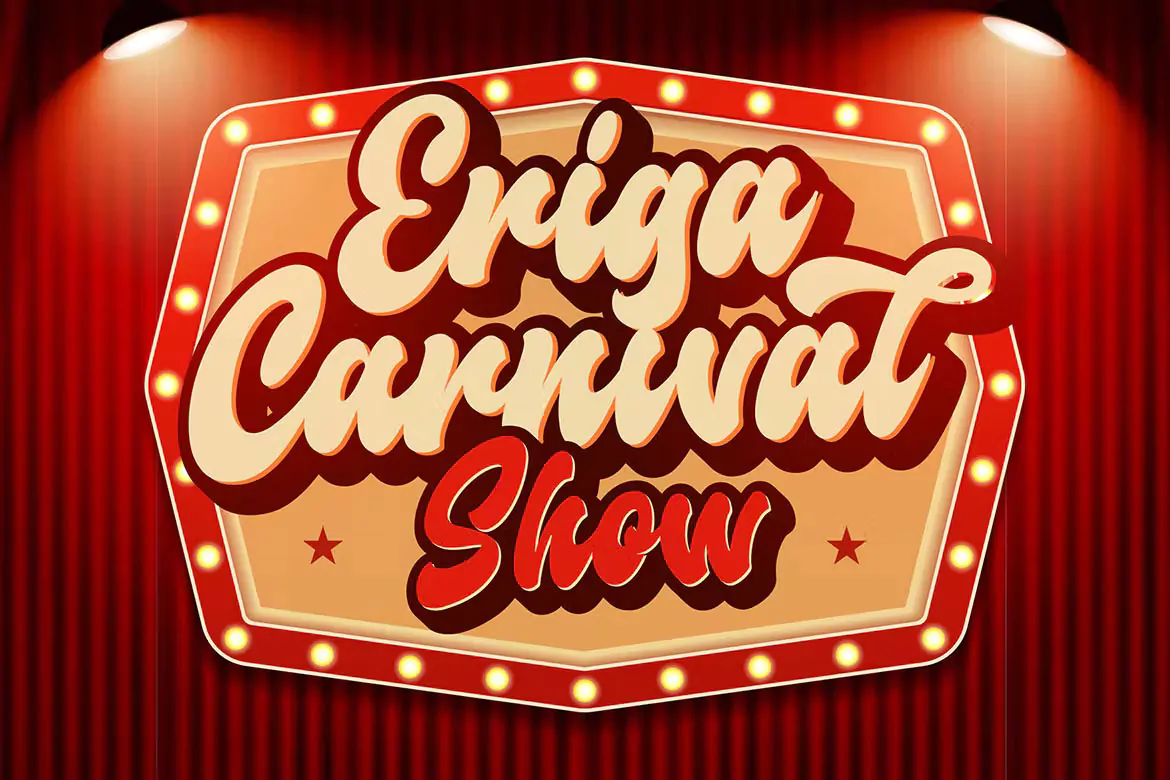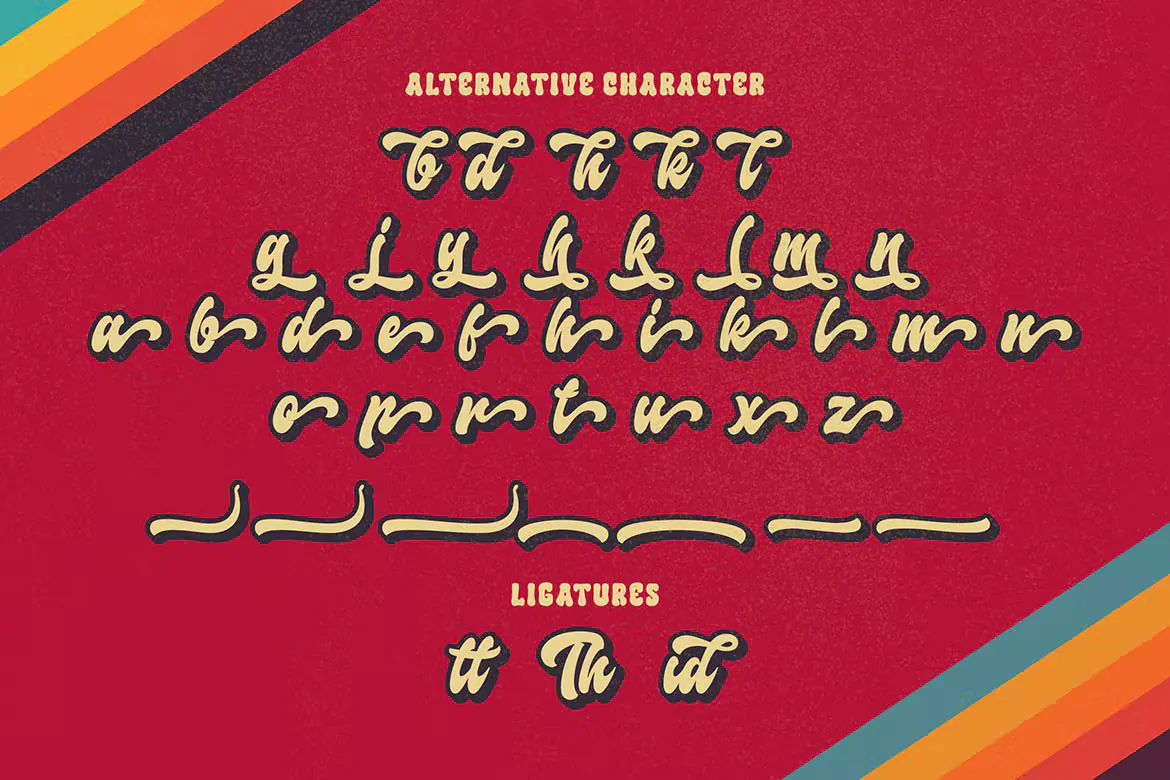
فونت قدیمی بولد Skyland
فونت قدیمی بولد و ضخیم
فونت قدیمی بولد Skyland یک اسکریپت فونت فوق العاده زیبا است که مناسب برای استفاده در طرح و پروژههای مختلف همچون طراحی صفحات وب، کارت ویزیت، بروشور، پوستر، بنر، بسته بندی محصولات و … میباشد.